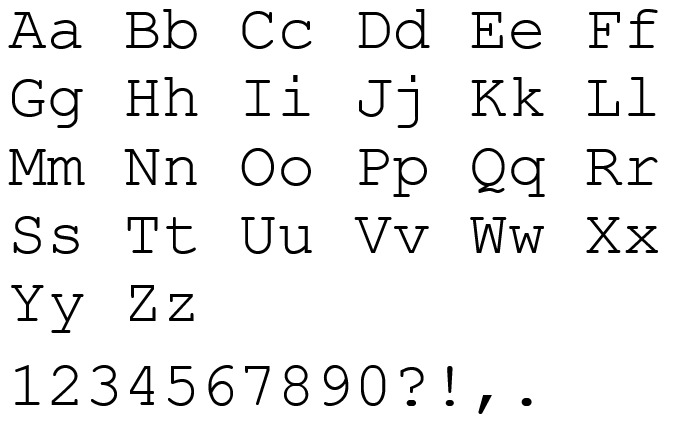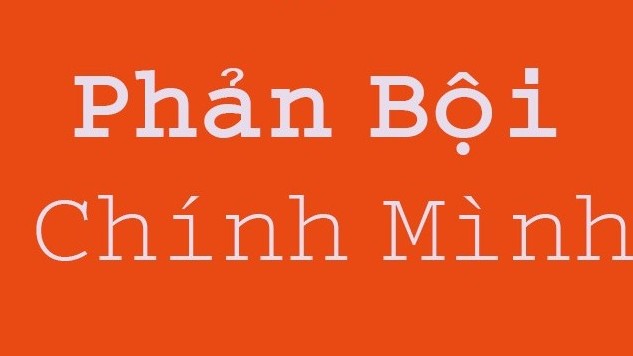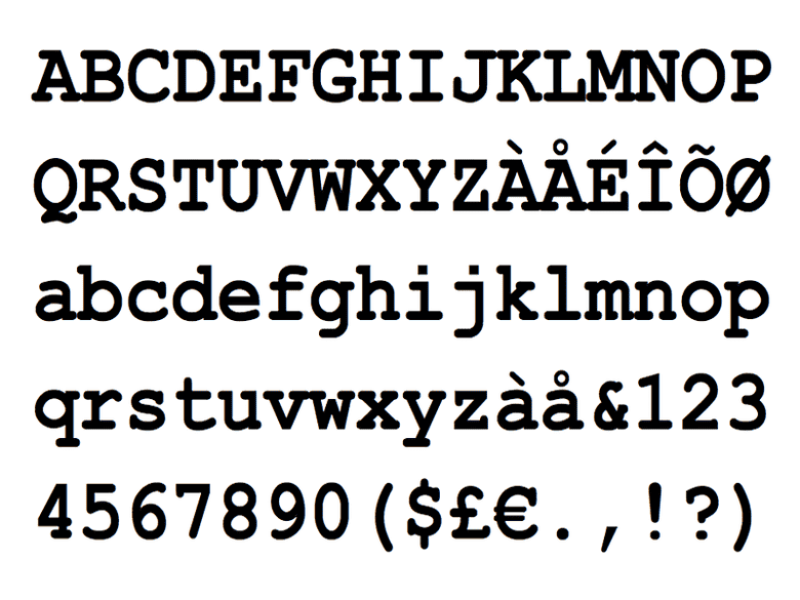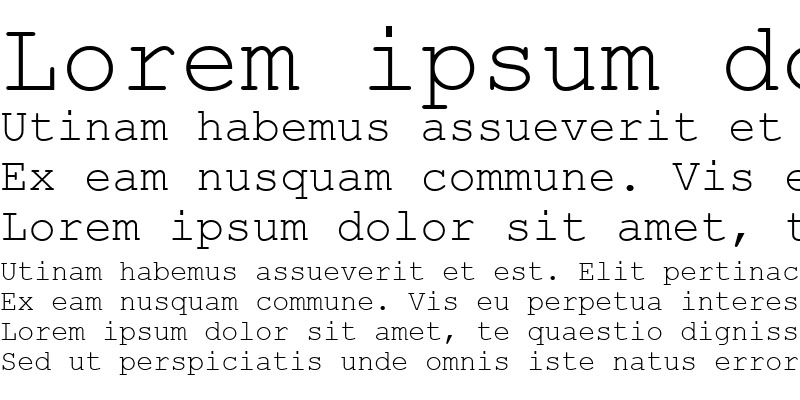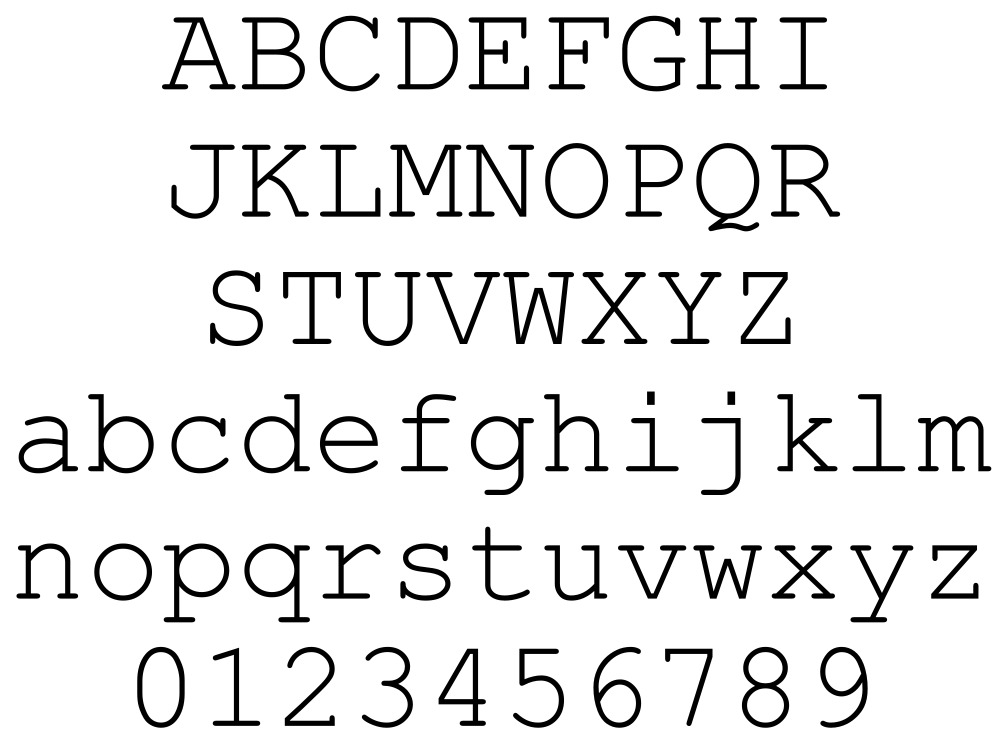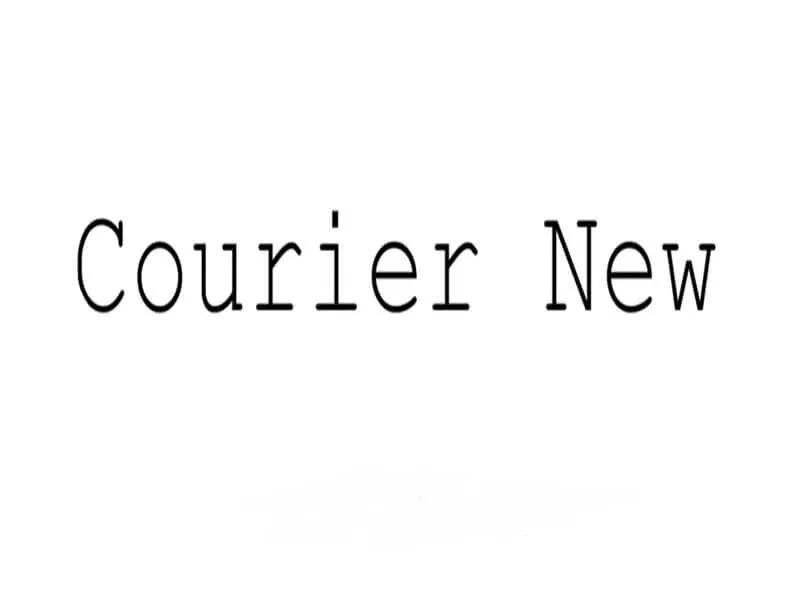
Nhiều người gặp rắc rắc khi sử dụng font Courier New Việt hóa bị lỗi bảng mã Unicode hoặc các ký tự có dấu hiển thị thô cứng, lệch dòng. Điều này khiến các bộ hồ sơ năng lực hay tem nhãn thông số kỹ thuật trở nên thiếu chuyên nghiệp, gây mất lòng tin với đối tác. Xưởng In Viva cung cấp bản font Courier New Việt hóa chuẩn, hỗ trợ sản xuất ấn phẩm văn phòng chất lượng cao.
Font Courier New Việt hóa là gì và phong cách máy đánh chữ kinh điển?
Courier New font Việt hóa là một phông chữ thuộc dòng Monospaced, nơi mọi ký tự đều có độ rộng bằng nhau tuyệt đối. Lấy cảm hứng từ những bản thảo máy đánh chữ IBM cổ điển, phông chữ Courier New mang lại cảm giác hoài cổ, vững chãi và cực kỳ minh bạch. Đây là lựa chọn hàng đầu cho các thiết kế yêu cầu tính chính xác cao như bảng mã lập trình, thông số kỹ thuật trên bao bì linh kiện hoặc các văn bản hành chính trang trọng.
Sức hút của dòng phông này nằm ở khả năng hiển thị rõ ràng, giúp người đọc dễ dàng đối chiếu số liệu mà không bị nhầm lẫn giữa các ký tự tương đồng. Bản tải font chữ Courier New tại In Viva đã được hiệu chỉnh kỹ thuật chuyên sâu, khắc phục hoàn toàn lỗi chân chữ và dấu thanh tiếng Việt. Việc sở hữu bộ phông chuẩn giúp designer tự tin triển khai các mẫu túi giấy đựng tài liệu hay hộp cứng đựng thiết bị điện tử với phong cách tối giản và hiện đại.
05 Ứng dụng phổ biến của font Courier New Việt hóa trong in ấn
Vẻ đẹp mộc mạc và tính chuẩn xác của mẫu chữ máy đánh chữ nâng tầm giá trị cho nhiều ấn phẩm truyền thông của đơn vị:
- Thiết kế bao bì thiết bị và linh kiện: Sử dụng phông chữ Courier New để in thông số kỹ thuật trên các dòng vỏ hộp giấy Ivory. Những nét chữ đơn cách tạo cảm giác minh bạch, giúp khách hàng tin tưởng vào độ chính xác của sản phẩm.
- Sản xuất bộ ấn phẩm văn phòng và hợp đồng: Chữ Courier New in trên tiêu đề thư hay phong bì tạo phong thái chuyên nghiệp, nghiêm túc. Đây là phông chữ kinh điển giúp các văn bản đối ngoại của công ty luật hay tài chính trở nên trang trọng hơn.
- Gia công in UV trên các hiện vật tri ân: Logo lồng ghép cùng kiểu chữ Courier New được in trên bình giữ nhiệt kim loại hoặc sổ tay da. Công nghệ in tại In Viva giúp các nét chữ hiển thị sắc sảo, bền màu theo thời gian sử dụng.
- Trang trí voucher và thẻ đặc quyền công nghệ: Một dòng chữ mang phong cách máy đánh chữ trên thẻ thành viên giúp tạo điểm nhấn độc đáo, gợi nhắc về tính nguyên bản và uy tín của nhãn hàng.
- Khắc laser tinh xảo trên bề mặt cứng: Sử dụng tải font chữ Courier New để khắc tên lên bút ký hoặc hộp gỗ. Tệp vector chuẩn giúp máy khắc đi nét mượt mà, tạo độ sâu sắc nét cho từng ký tự Serif.
04 lưu ý kỹ thuật khi sử dụng font Courier New Việt hóa phục vụ sản xuất
Để hệ thống ký tự đơn cách hiển thị sống động và bền màu trên các thành phẩm thực tế như túi giấy hay quà lưu niệm, designer cần chú trọng:
- Kiểm soát mật độ chữ trong dàn trang: font Courier New Việt hóa chiếm khá nhiều diện tích chiều ngang. Designer nên điều chỉnh khoảng cách dòng (Leading) hợp lý để văn bản trên catalogue không bị dày đặc, gây khó đọc cho khách hàng.
- Tối ưu đường Path cho gia công bế nổi: Bước này đặc biệt quan trọng khi sản xuất nắp hộp cứng dập nổi logo doanh nghiệp theo phong cách Courier. Kỹ thuật viên cần làm mượt từng điểm neo vuông vức trong file vector giúp khuôn bế thực hiện chính xác, không làm rách giấy.
- Thiết lập hệ màu CMYK chuẩn in ấn: Designer cần hiệu chỉnh hệ màu CMYK chuẩn tại xưởng và yêu cầu in mẫu thử để đảm bảo màu chữ sau in không bị ám xám hay mất sắc độ, đặc biệt là trên chất liệu giấy Kraft nâu.
- Điều chỉnh độ dày nét theo vật liệu: Khi in trên các bề mặt có độ bóng cao như inox hay nhựa sinh học, bạn nên chọn biến thể Bold để chữ không bị lóa và giữ được độ sắc sảo dưới ánh sáng mạnh.